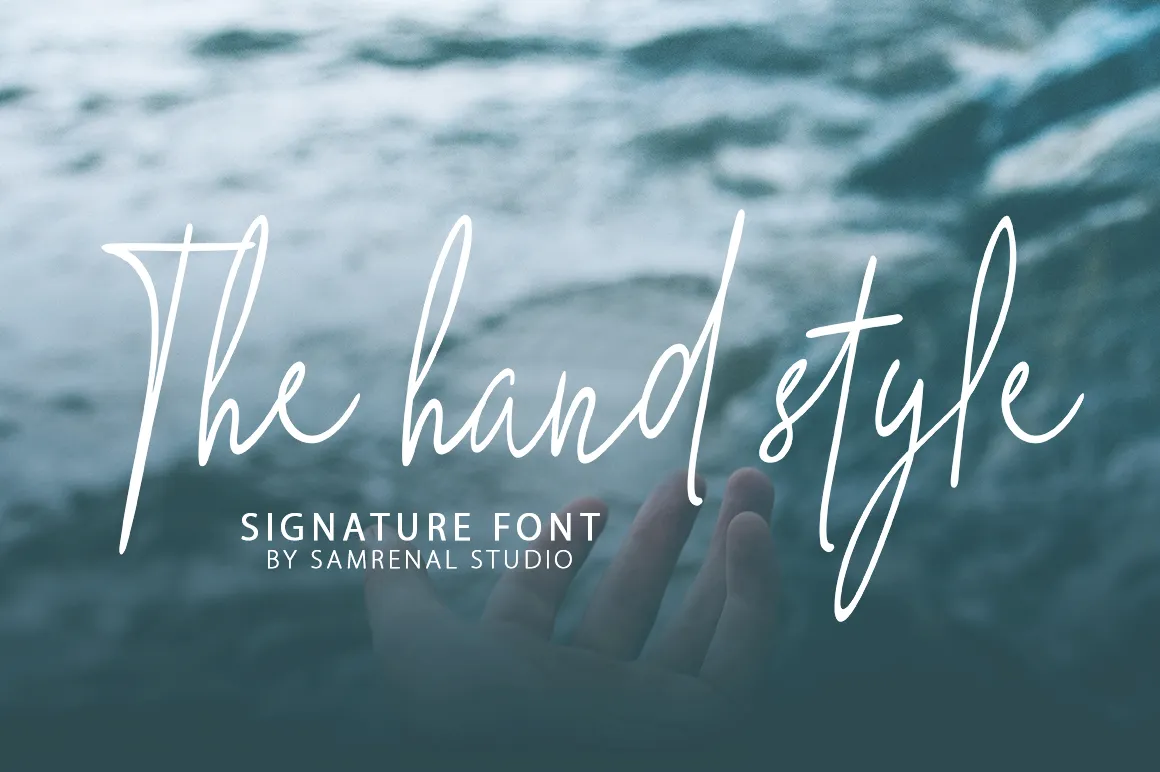
The Hand Style Script Font – Download Grátis
Através de The HandStyle Font Script você tem a chance de dar vida à sua criação com uma escrita artesanal perfeitamente equilibrada e casual. Esse é um tipo de fonte que resgata aquele toque pessoal, oferecendo um ar elegante e moderno que certamente impressionará seus destinatários. Perfeito para logotipos, cartões de agradecimento, identidades corporativas, citações, impressões digitais e até mesmo encomendas personalizadas, The HandStyle atua como uma adição única ao seu projeto. Suas letras minúsculas incluem alternativas, finalizações em swashes tanto no início quanto no fim, garantindo um resultado visualmente impressionante que definitivamente destacará o design. Com The HandStyle Font Script, você não apenas torna sua peça de design mais atraente e especial, mas também adiciona uma sensação personalizada única, criada com cuidado para cada detalhe.